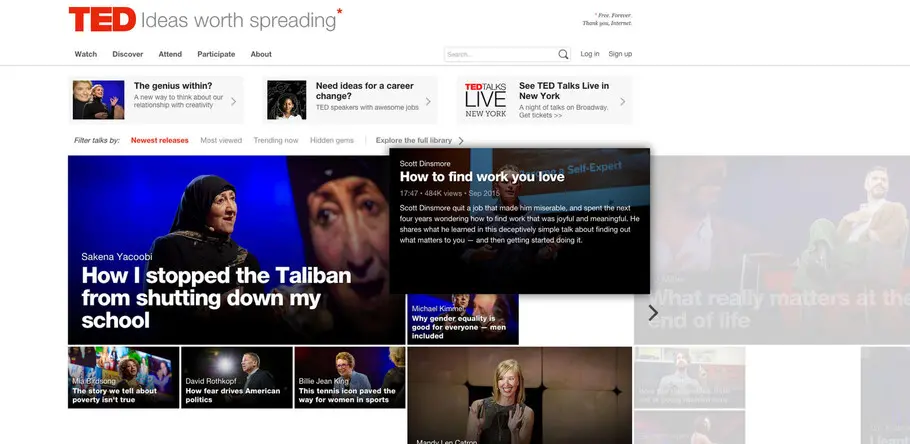
Neue HelveticaがTEDのために本領を発揮
「 TED.com is a standout example of how the oft-criticized elements of Helvetica can become essential requirements. 」
7年ぶりにウェブサイトのデザインを変更したTED(Technology Entertainment Design)は、TED TALKで語られる情熱的なスピーチとその素晴らしいアイデアを伝えるのにふさわしい書体としてNeue Helveticaを採用しました。
TEDのウェブサイト(TED.com)は2007年に制作されて以降、昨年初めてデザインを変更しました。ニューヨークシティのオフィスでTEDの担当者のみなさんにお会いした際には、以下のような話がありました。
「デジタルの世界にとっては2007年はかなり昔のこと。TEDが組織として成長し、ウェブサイトのコンテンツが増えるにつれて、時代遅れのウェブサイトになっていきました」
今回のTED.com(ウェブサイト)のリニューアルは、単なるウェブサイトの作り変えではなく、もっと大きなことをするつもりでした。TEDでは、既存のウェブサイトの構造の問題点を一時的に解消するのではなく、これまでになかった「デジタル的な」拠り所となるウェブサイトを作る必要がありました。
「我々は強い意志を持って技術的なプラットフォームのフロントエンドとバックエンドを再構築し、メディアの動きや変化にも対応できるウェブサイトを構築したかったのです」とTEDの製品開発ディレクターのThaniya Keereepartは述べています。
「我々はレスポンシブ デザインが当たり前になった今、ウェブサイトのデザインを刷新する大きな決断をしました」
ウェブサイトでは、TEDカンファレンスで用いられる既存の視覚的な言語を念頭におく必要がありました。
「デザイン面では、デザインをより進化させるアプローチをとるようにしました。TEDでは独特の視覚的な言語が用いられており、これまでとてもよい効果を発揮してきました。デザインを改変する際、ミニマリズム、余白、グリッドデザインの原理をベースにし、その多くは変更しないように心がけました。それは私たちが大切にしているTEDの歴史の移り変わりなのです」とTEDのデザインサービスディレクターであるMike Femiaは述べました。
まず約6ヶ月に渡り、それまでにいただいたウェブサイトに関する膨大な数のメールや広範囲におよぶアンケートを徹底的に研究しました。その後、その過程をブログに詳細に記録しました。この工程を終えるのに約1年かかりました。
「我々はTEDコミュニティに関わる多くの方々、例えば催し物の主催者、通訳者、スピーカー、参加者、熱心なTEDファンの方と話をしました。そして引き続きTEDコミュニティを活用し、デザインを新しくする過程で、ユーザからのさまざまな評価をいただきました」とThaniyaは説明しました。
TEDコミュニティとの深い関わりによってわかったことは、TEDコミュニティが求めているデザインとデザインチームが目指すデザインの方向性は一致していたということでした。つまり、中立的な立場を持ちながらTEDのコンテンツを更新する環境を整え、TEDの内容を妨げることのない空間を作ることでした。TEDのウェブサイトのデザインは、見せるためのものではなく、(ウェブサイトにアクセスする)ユーザとの間の橋渡しになる必要があったことは始めから明らかでした。
デザインチームは、過去にTEDカンファレンスがアートとデザインの面でウェブサイトよりも先行していたことを認めています。そして、今回ウェブサイトをリニューアルするにあたり、それまであったギャップを解消するつもりでした。
「これまではシステムスタックフォントを使い、何とかやってきましたが、それはTEDブランドには不十分なものでした。今後はTEDカンファレンス側で行われていることすべてをウェブサイトでも確実に行うようにしたいのです。これは今後も継続して行なっていきたいことで、われわれが損ねたくないと思っている最も大切な美学についても言えることなのです」
とデザインチームの主任UXデザイナーのAaron Weyenbergは述べています。
「 今回リニューアルされたウェブサイトTED.comでは、Helveticaフォントを採用したことでよく批判を受けますが、その批判される要素が実はTED.comにとっては最も必要とする要件であるという優れた事例ができました。 」
TEDが最も大切にしている美学の1つがフォントです。TEDカンファレンスでは、初期のころからHelvetica®をTED TALKやブランドの書体として用いてきました。TEDのオリジナルロゴは、Neue Helvetica®をベースに作られています。しかし、Helveticaに対して批判が向けられること、それはTEDにとっては強みになります。
「Helveticaに対して向けられる批判は、すべてが強みになります。批判の声はHelveticaが冒険をしない面白みのないフォントであるということなのですが、それは我々にとっては強みなのです。なぜならば主役であるスピーカーのアイデアをHelveticaが妨げることは絶対にないのですから」とMikeは述べます。
TEDは書体に対する敬意についても明確で、「Helveticaは極めて美しく明瞭な書体で、たとえどんなに一般的に使われ、平凡で退屈なフォントであると言われても、デザイン面においては普遍的で完成された書体なのです」
Helveticaだからこそ、一歩下がってTEDがうまくいくように見守ることができたのです。とAaronは述べ、さらに以下のように説明しました。
「Helveticaはどちらかと言えば特徴のない書体です。そしてTEDで成し遂げようとしていることは、アイデアのアーカイブを作ることであり、トレンディーなことをしようとしているわけではありません。ですからある意味流行り廃りのないものにしたいと思っています」
Aaronは続いて、TEDの写真や動画や画像にはインパクトがあるが、ウェブサイトのコンテンツはある程度インパクトを抑える必要があると述べています。
「コンテンツがより実用的になります。Helveticaは今でも見事なフォントで、様々な種類のHelveticaを使えば、指示書から報告書、音声の書き起こしにいたるまで、それぞれの書面に合ったトーンに調節することができます。Helveticaは目立たずにさまざまなことを可能にしてくれるのです」
Helveticaは、他の美学を受け入れるための空間を提供し、TEDチームがある程度実験することを可能にしてくれます。
今回ウェブをリニューアルするプロジェクトでTEDは創造性に富んだHuge社と提携しました。デザインチームは、さまざまなフォントの太さと行間隔でテストを行い、ウェブサイトに掲載される多様なコンテンツに対応する書体としてHelveticaがふさわしいことを証明しました。また編集側の要望として、名称やヘッドラインの長さなども考慮に入れています。
「イタリック体やヘッダーなどの扱い方は時間とともに微妙に変わりますが、扱うフォントはHelveticaから変わることはありません」とMikeは述べました。
TEDは幅広い言語を扱いますが、それに対応できるフォントとして選ばれたHelveticaが広範囲の言語をサポートすることできるということも重要な要素の1つでした。
今回リニューアルされたウェブサイトTED.comでよく受けるHelveticaフォントを採用したことへの批判要素は、実はTED.comにとって最も必要とされる要件であるということを示す好例となりました。ウェブサイトのデザインが不可欠な要素でありながら、サポートとしての役割を求められるとき、Helveticaは本領を発揮します。
「TEDはデザインを専門とする組織ではありません」とMikeは結論づけました。
「TEDはアイデアを創出する組織です。ですから我々にとって、デザインはアイデアを支えるものであり、それが我々のコミュニケーションのすべてなのです」